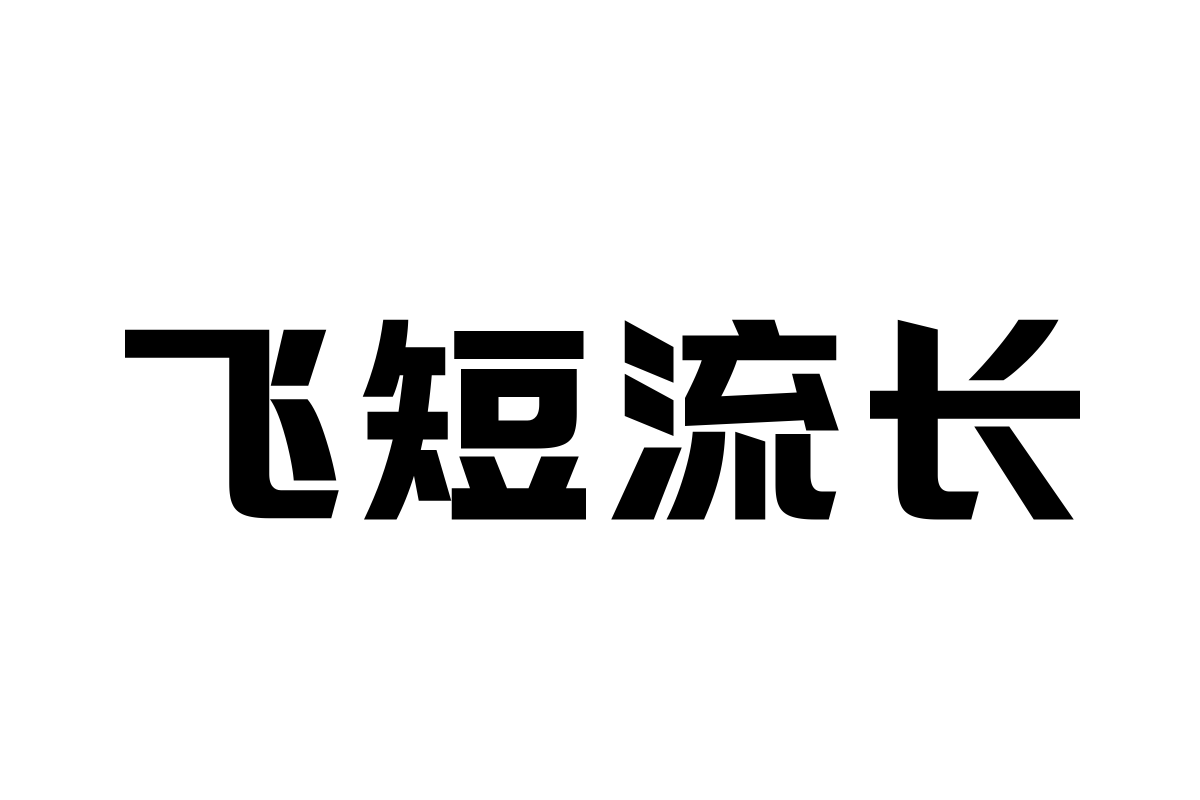
三极力量酷黑 极粗字体是一款专为需要强调文字的场合设计的粗体字体。这款字体具有独特的设计风格,能够吸引观众的注意力,提高信息的传达效果。它的线条粗犷有力,给人一种强烈的视觉冲击感,非常适合用于广告、海报、宣传册等需要突出显示文字的场合。同时,三极力量酷黑 极粗字体也适用于网站设计、网页标题、按钮等需要强调文字的场合,能够提升整体的视觉效果。